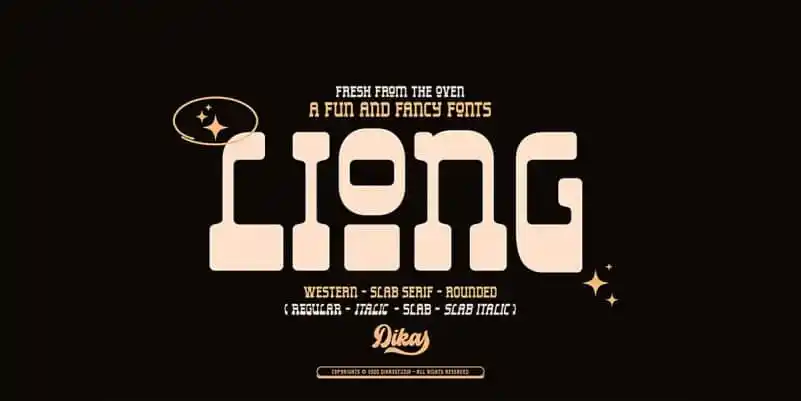
Liong Display Font – Download Grátis
Olha quem chegou! Introduzimos a Liong Display Font para vocês amantes do tipo. Inspirada num design minimalista e geométrico, essa é uma fonte slab serif criada por Andika Setiawan. Liong Display é uma mistura de estilos clássicos com nuances decorativas do estilo slab da década dos 60 e 70. Este design é tão versátil que se adequa perfeitamente a logotipos, selos, tipografia e qualquer projeto retro. Com um barra de peso única e linhas grossas em destaque, esta fonte oferece alta contraste para um resultado impecável. Liong traz 4 estilos: regular, itálico, slab e salab italic. Perfeito tanto para uso pessoal quanto profissional, é uma escolha inteligente para quem deseja incorporar um toque nostálgico a seus projetos digitais. Ideal tanto para personalizar sua identidade visual quanto para criar designs retro que remetem à era dos anos 60 e 70. Não perca esta oportunidade de enriquecer seu projeto com uma fonte tão única e versátil como a Liong Display Font.